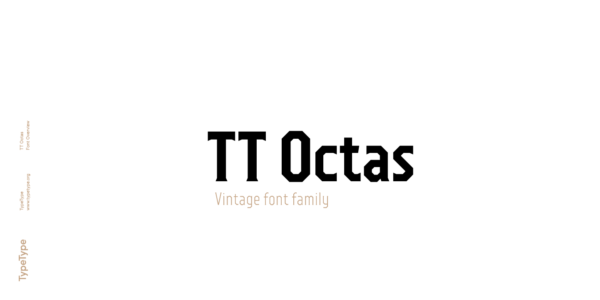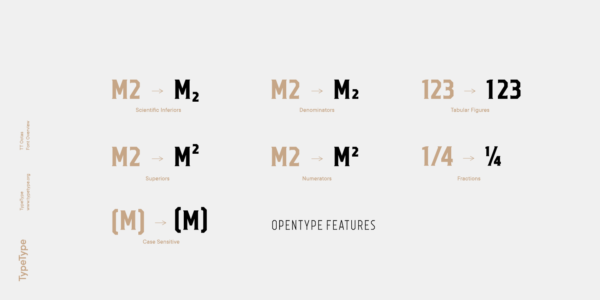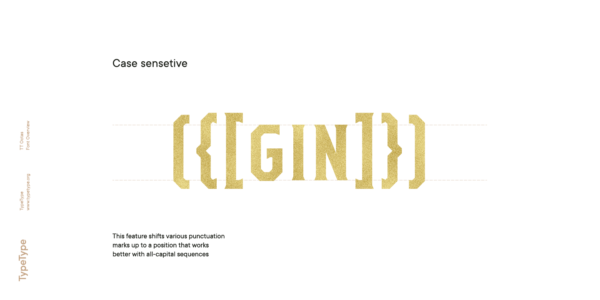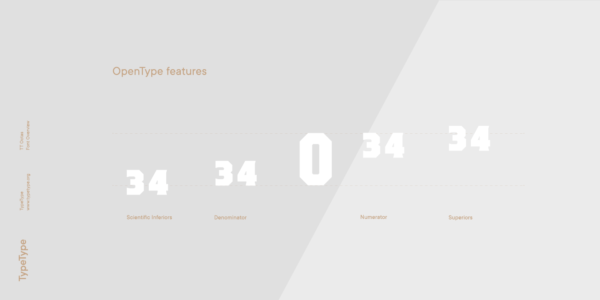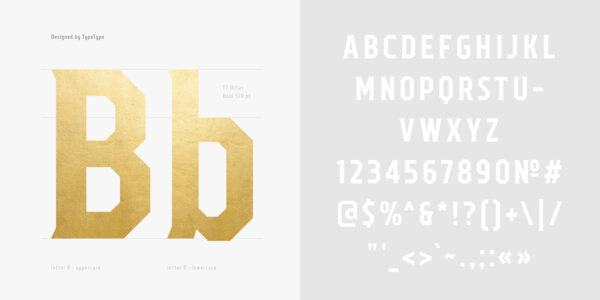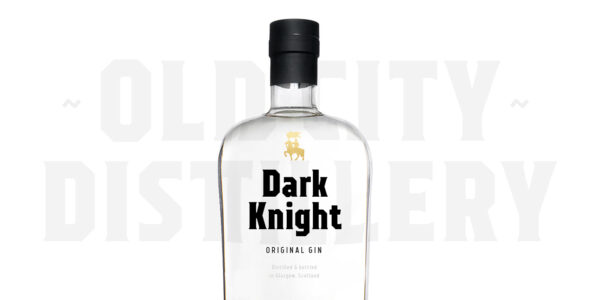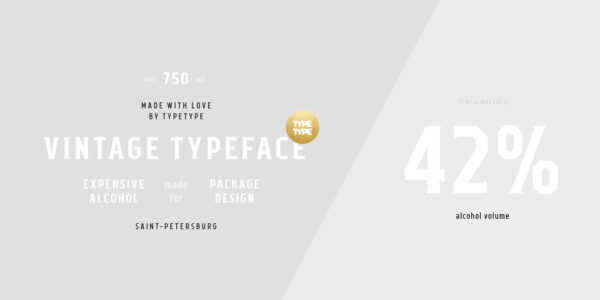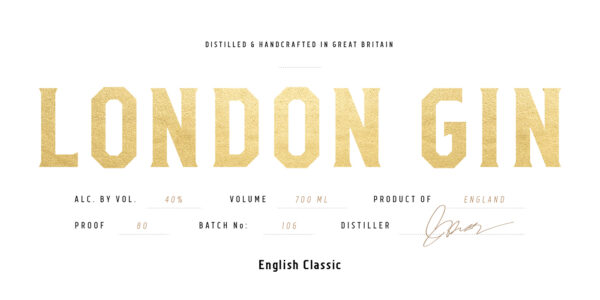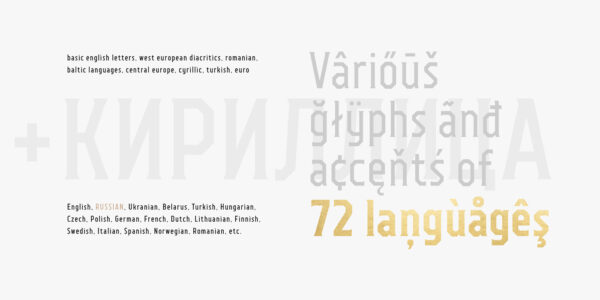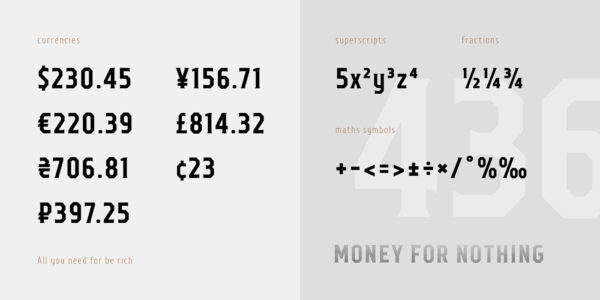
TT Octas
TT Octas — ТТ Октас
Произносится «ТТ Октас». «Octas» — производное слово от octa, в переводе с греческого «восемь». Буквы «TT» являются аббревиатурой названия компании.
TT Octas — октогональный шрифт с узкими пропорциями и небольшими засечками, которые придают ему необычный характер и отголосок чего-то старинного.
TT Octas
Шрифтовое семейство с узкими пропорциями
TT Octas
Простой рисунок букв и засечки позволяют шрифту хорошо считываться даже в самых маленьких размерах. Узкие пропорции позволяют умещать большие массивы текста в небольших текстовых блоках. Данная шрифтовая гарнитура хорошо подходит для айдентики и маркировки товаров, а также всех цифровых носителей, например веб-интерфейсов и геймплеев игр, а также хорошо подойдет для интерфейсов мобильных приложений.
TT Octas
TT Octas построен по принципу октагональности — все окружности представляют из себя восьмигранники
TT Octas
TT Octas имеет насыщенный и старинный характер
О гарнитуре TT Octas
TT Octas — шрифтовое семейство с узкими пропорциями, построенное по принципу октагональности, в данной гарнитуре все окружности представляют из себя восьмигранники. Благодаря небольшим засечкам Октас приобретает насыщенный и старинный характер. Простой рисунок букв и засечки позволяют шрифту хорошо считываться даже в самых маленьких размерах.
Узкие пропорции позволяют умещать большие массивы текста в небольших текстовых блоках. Данная шрифтовая гарнитура хорошо подходит для айдентики и маркировки товаров, а также всех цифровых носителей, например веб-интерфейсов и геймплеев игр, а также хорошо подойдет для интерфейсов мобильных приложений.
case | Case Sensitive Forms
({[H]})
frac | Fractions
1/2 3/4
numr | Numerators
H123
dnom | Denomerators
H678